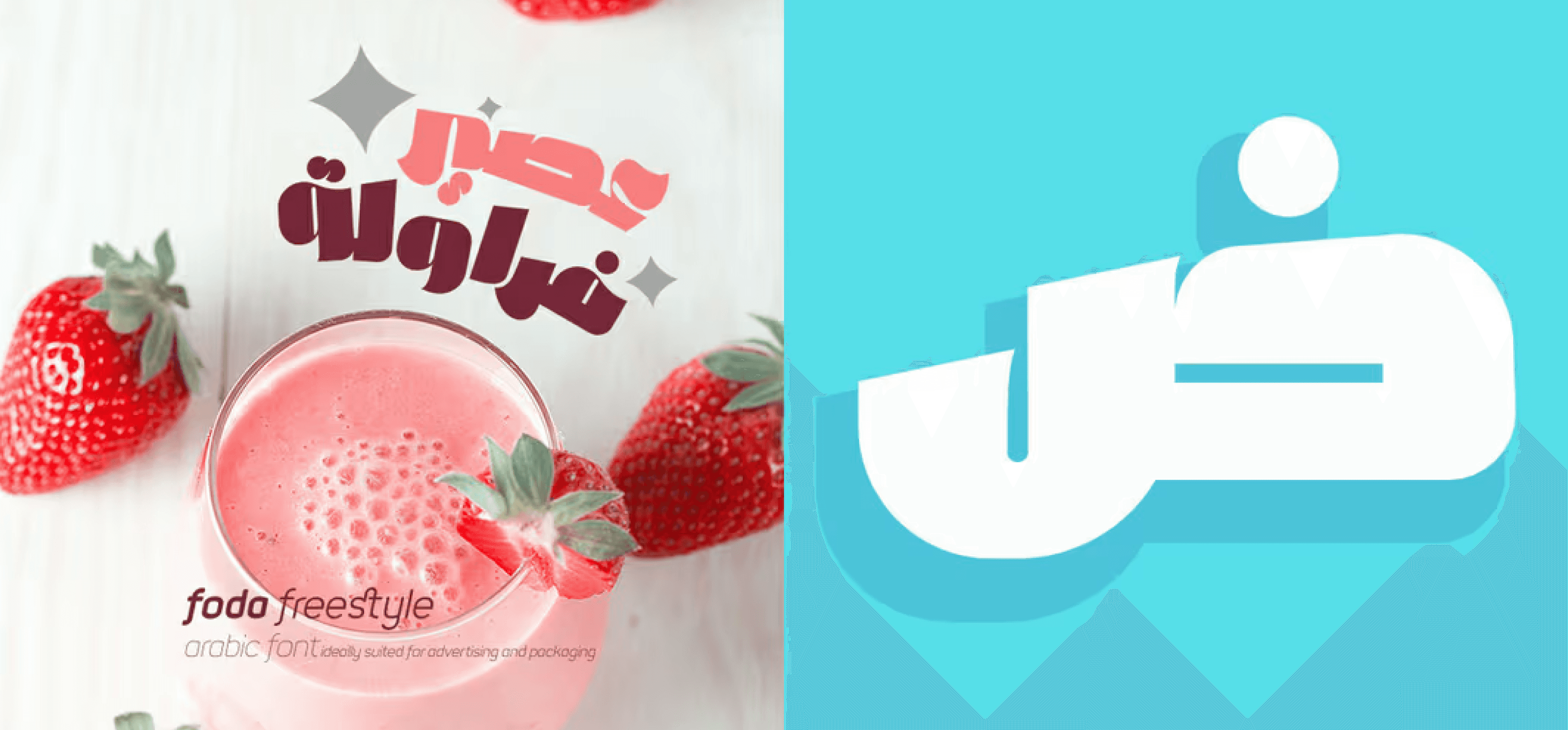
هو خط عرض عربي يتميز بتباين عالٍ يمنحه حضورًا بصريًا قويًا يجذب الانتباه بكل تأكيد.
يأتي بوزن واحد، ويُستخدم في العناوين الرئيسية، العناوين الفرعية، الملصقات، الإعلانات، والعديد من الاستخدامات الأخرى.